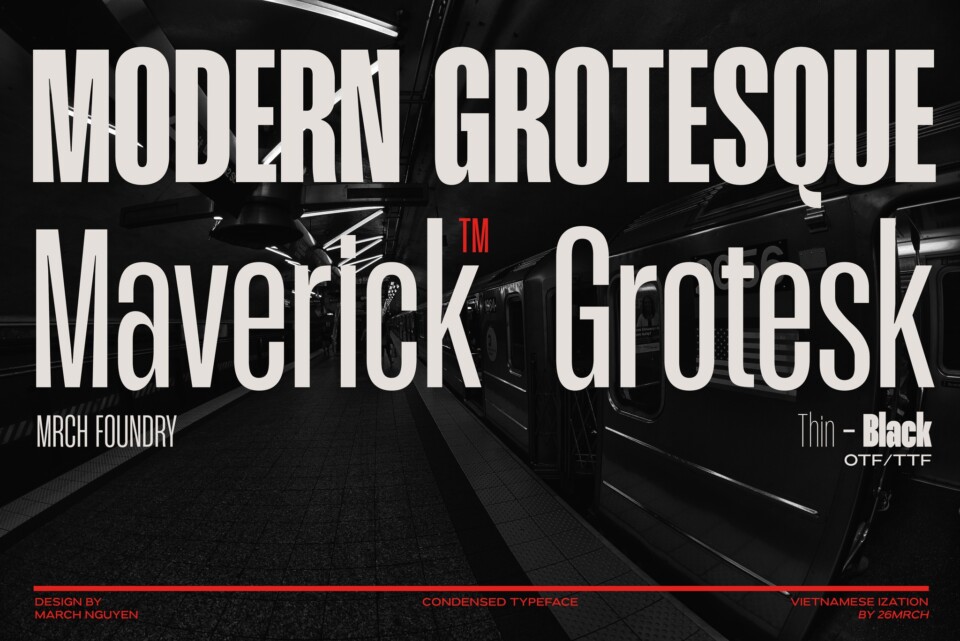
Font Tiếng Việt Maverick Grotesk – March Nguyen
Font Tiếng Việt Maverick Grotesk – March Nguyen – Bộ Font Hiện Đại Cho Thiết Kế Việt
Giới thiệu về Font Tiếng Việt Maverick Grotesk – March Nguyen
Trong thế giới đồ họa hiện đại, việc lựa chọn một Font Miễn Phí chất lượng luôn là ưu tiên hàng đầu của các nhà thiết kế. Font Tiếng Việt Maverick Grotesk – March Nguyen nổi lên như một giải pháp hoàn hảo, kết hợp giữa phong cách Sans Serif truyền thống và hơi thở đương đại. Được tinh chỉnh kỹ lưỡng bởi tác giả March Nguyen, bộ font này không chỉ đảm bảo tính thẩm mỹ mà còn mang lại trải nghiệm đọc tuyệt vời trên mọi nền tảng kỹ thuật số và in ấn chuyên nghiệp.
Đặc điểm nổi bật của bộ font
Đặc trưng lớn nhất của Font Tiếng Việt Maverick Grotesk – March Nguyen chính là cấu trúc hình học cân đối và các đường nét dứt khoát. Bộ font hỗ trợ đầy đủ bảng mã tiếng Việt, giúp người dùng không còn lo lắng về lỗi hiển thị dấu hay khoảng cách ký tự. Với nhiều trọng lượng khác nhau từ Thin đến Black, bạn có thể linh hoạt sử dụng cho tiêu đề bài viết, thiết kế logo hoặc trình bày nội dung sách báo một cách khoa học.
Ứng dụng thực tiễn của Font Tiếng Việt Maverick Grotesk – March Nguyen
Nhờ vẻ ngoài tối giản và sang trọng, Font Tiếng Việt Maverick Grotesk – March Nguyen cực kỳ phù hợp cho các dự án nhận diện thương hiệu công nghệ hoặc thời trang. Đối với học sinh và sinh viên, đây là công cụ hỗ trợ đắc lực trong việc làm slide thuyết trình hay trình bày tiểu luận, giúp nội dung trở nên chuyên nghiệp và thu hút hơn. Sự rõ ràng của các chữ cái giúp người xem dễ dàng tiếp nhận thông tin mà không gây mỏi mắt.